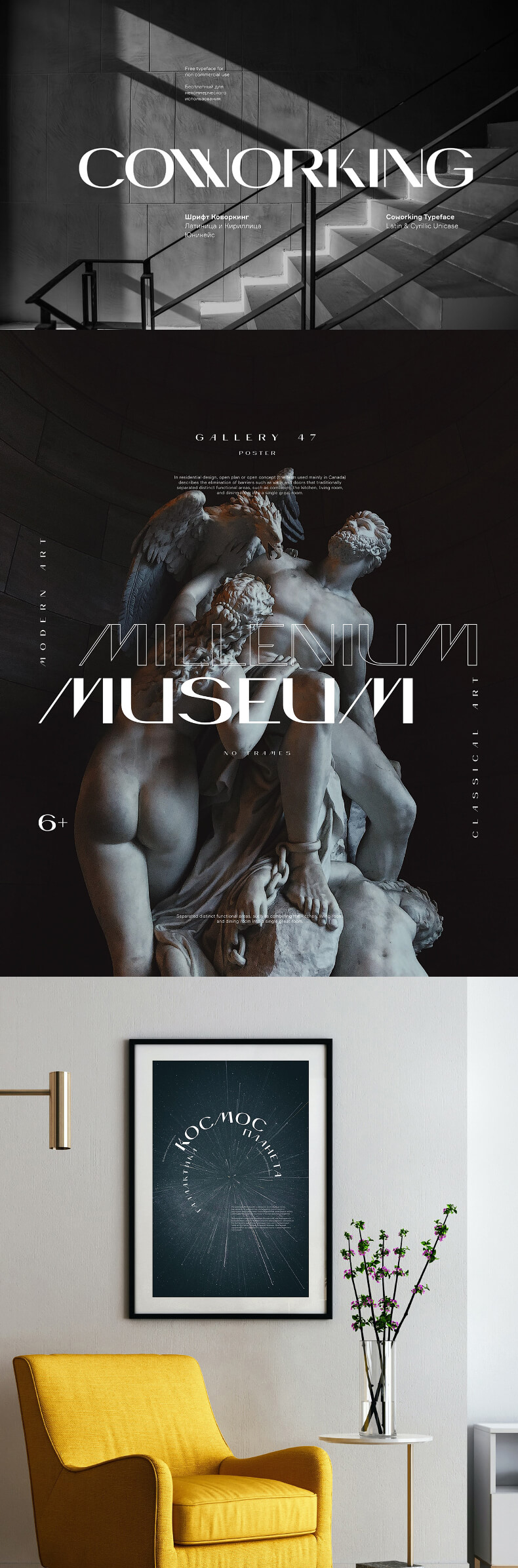
Шрифт - Коворкинг/Coworking
Коворкинг - стильный шрифт без засечек для дизайна логотипов и заголовков. Поддерживается кириллица и латиница. Отображение символов только Caps (заглавные).